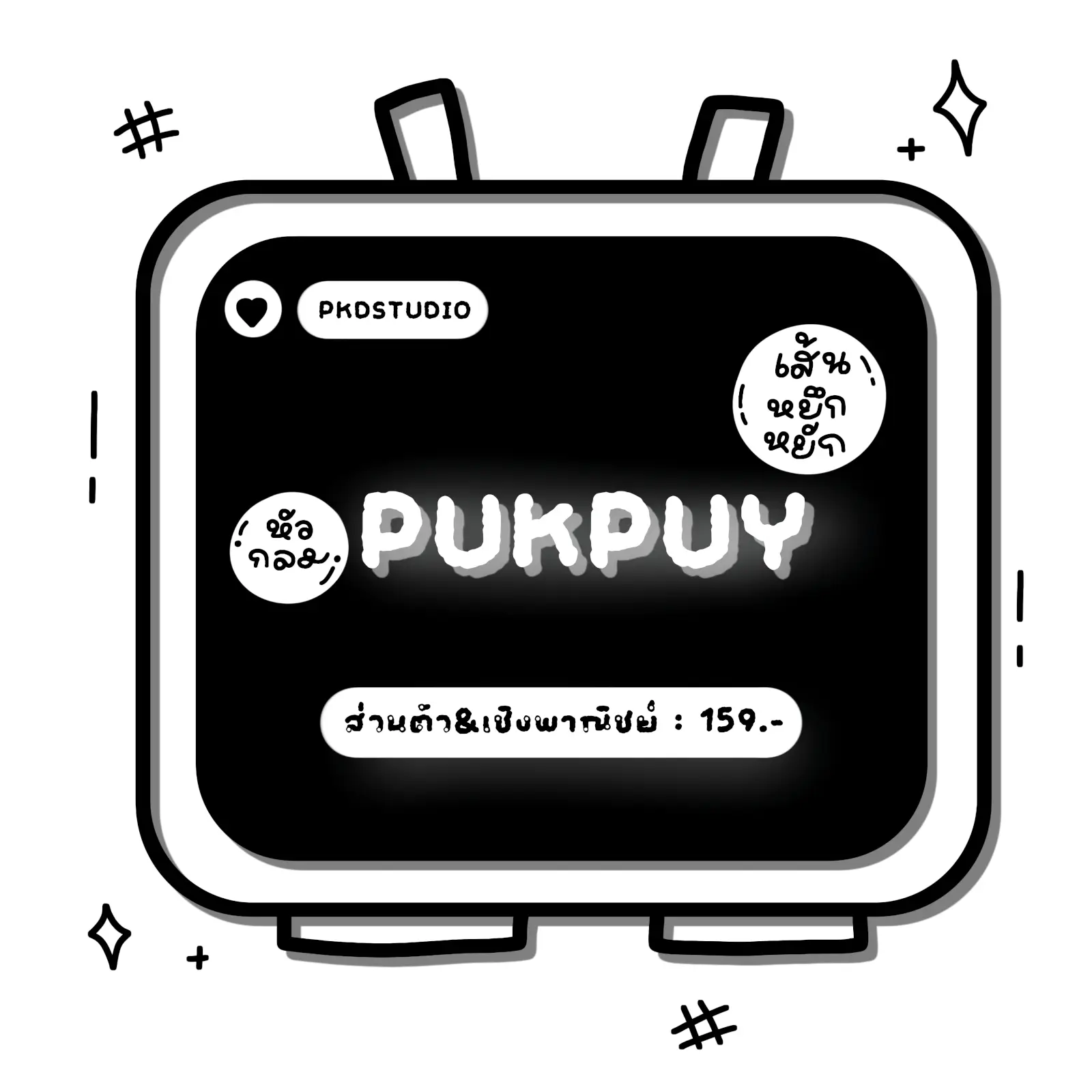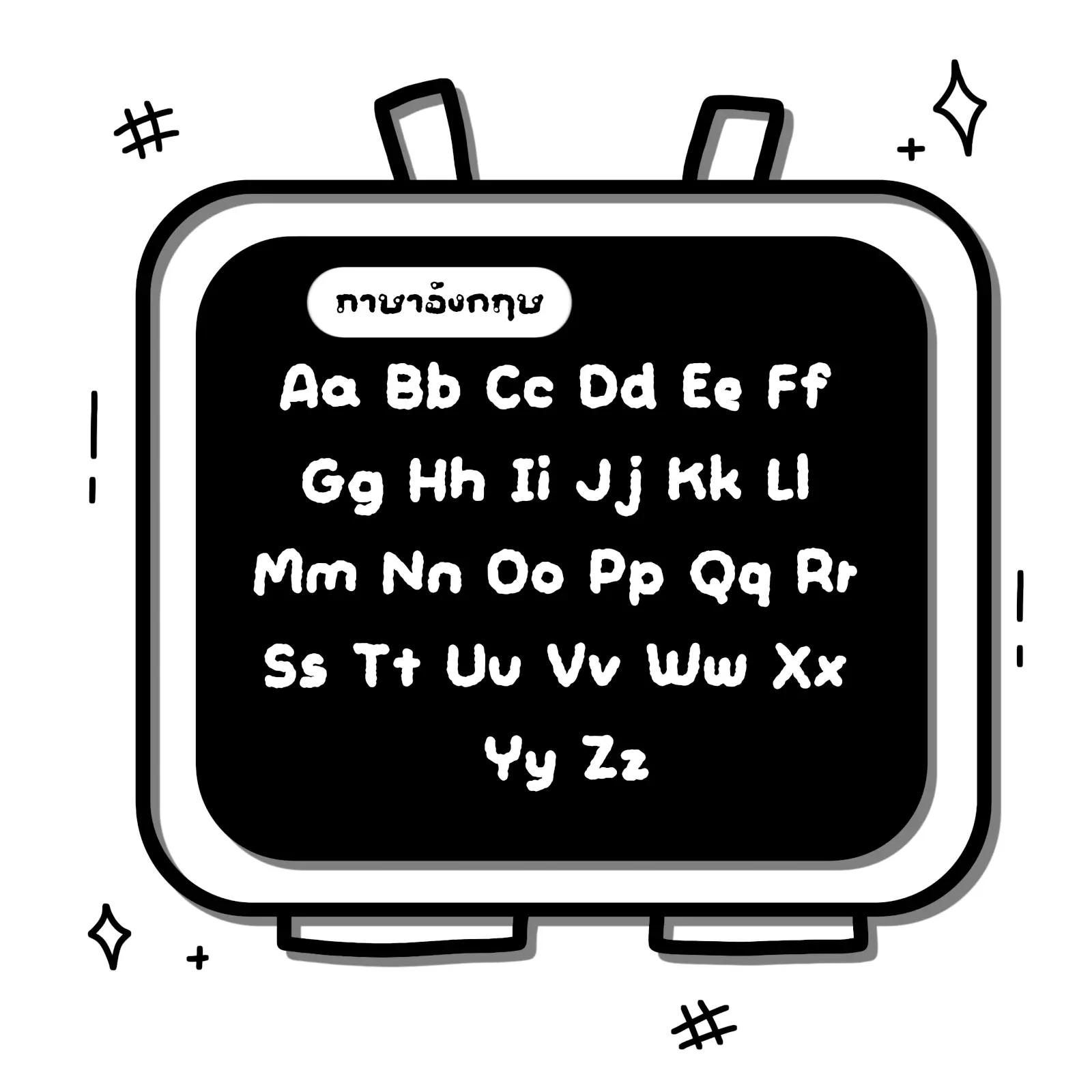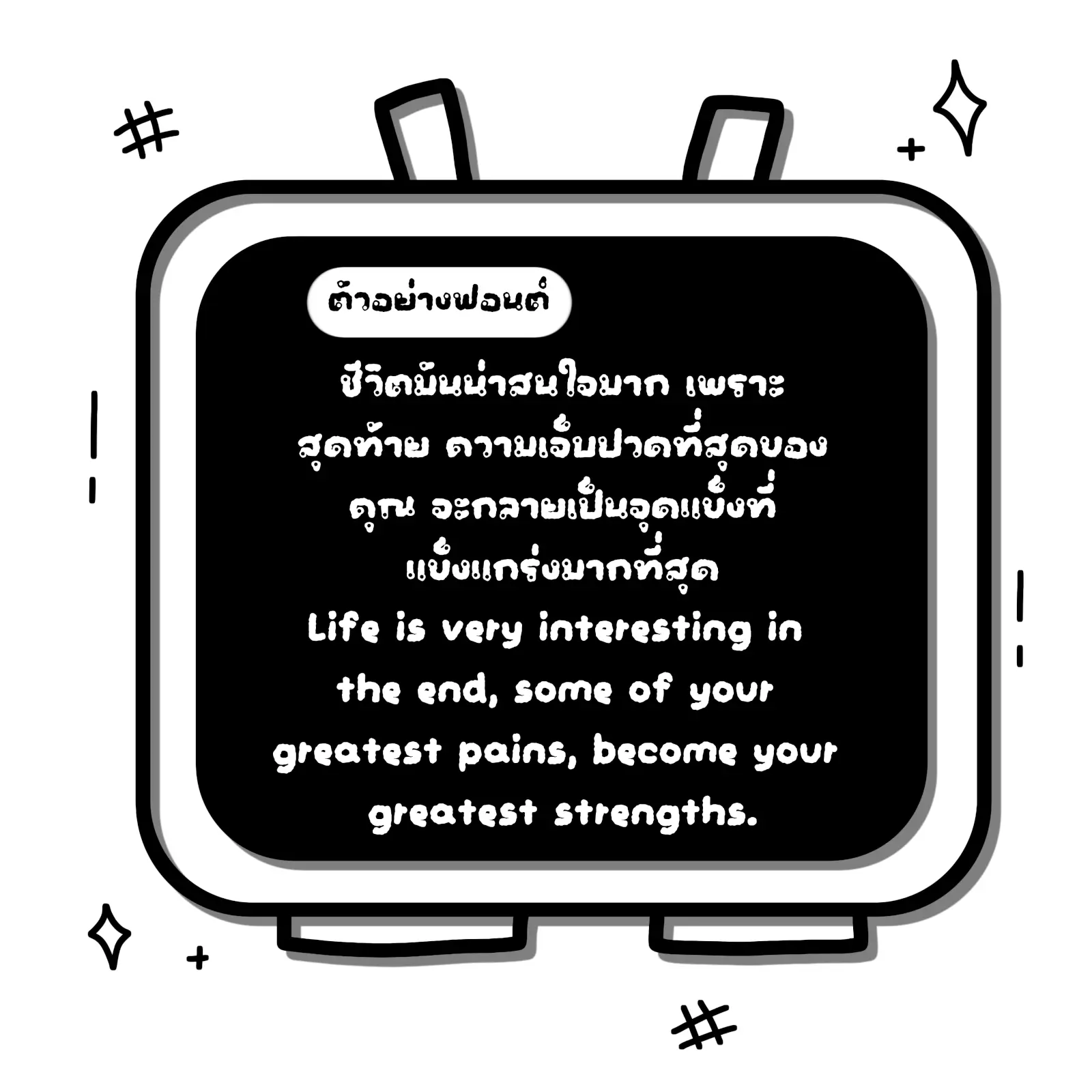
ปุกปุยฟอนต์ (PKD PUKPUY) – ฟอนต์ลายมือน่ารัก สดใส เป็นกันเอง เหมาะสำหรับงานคอนเทนต์ โพสต์โซเชียล สติกเกอร์ คาเฟ่ และงานออกแบบทั่วไป
- ไม่มีตัวอักษรโปร่งผสม
- รองรับภาษาไทย ภาษาอังกฤษ ตัวเลข และสัญลักษณ์
ปุกปุย (PKD PUKPUY)